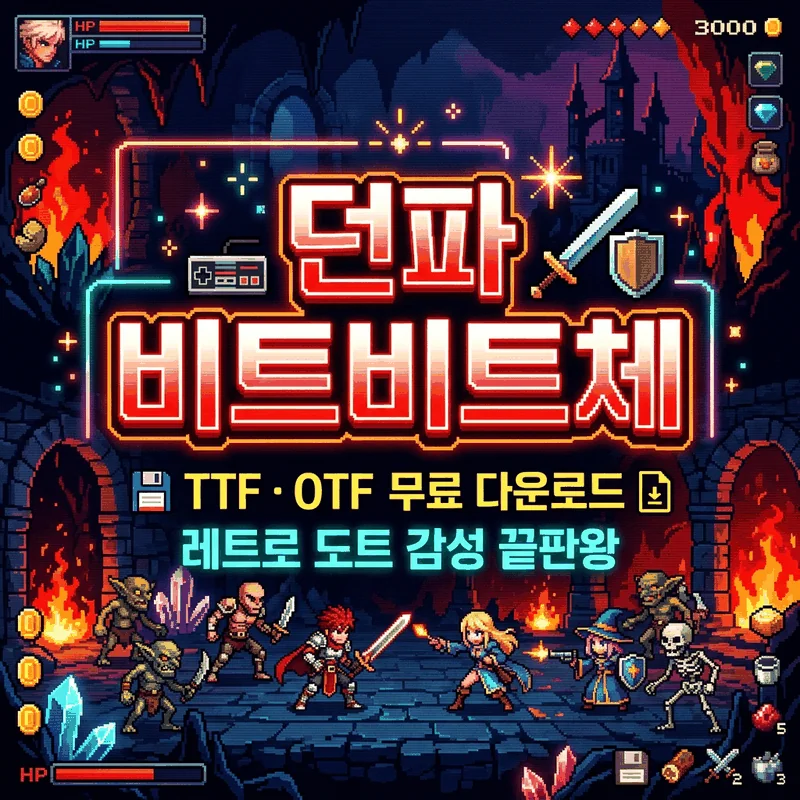
8๋น„ํŠธ ๋ ˆํŠธ๋กœ ๊ฐ์„ฑ์˜ ์ •์  '๋˜ํŒŒ ๋น„ํŠธ๋น„ํŠธ์ฒด v2'์˜ ํŠน์ง•, ๊ณต์‹ ๋‹ค์šด๋กœ๋“œ ๊ฒฝ๋กœ, ์ƒ์—…์  ํ—ˆ์šฉ ๋ฒ”์œ„, ๊ทธ๋ฆฌ๊ณ  ์Šค๋งˆํŠธํฐ ์ ์šฉ๋ฒ•๊นŒ์ง€ ์™„๋ฒฝํ•˜๊ฒŒ ์ •๋ฆฌํ–ˆ์Šต๋‹ˆ๋‹ค.
๋„ํŠธ ๊ฐ์„ฑ, 8๋น„ํŠธ ๊ฐ์„ฑ, ํ”ฝ์…€์•„ํŠธ ์Šคํƒ€์ผ ๋””์ž์ธ์„ ํ•  ๋•Œ ์–ด์šธ๋ฆฌ๋Š” ํ•œ๊ธ€ ํฐํŠธ๋ฅผ ์ฐพ๋‹ค ๋ณด๋ฉด ์„ ํƒ์ง€๊ฐ€ ์ƒ๊ฐ๋ณด๋‹ค ๋งŽ์ง€ ์•Š์Šต๋‹ˆ๋‹ค. ๊ทธ์ค‘์—์„œ๋„ ๋˜ํŒŒ ๋น„ํŠธ๋น„ํŠธ์ฒด๋Š” ์ง„์งœ ๊ฒŒ์ž„ ์ œ์ž‘์‚ฌ์˜ ์›น๋””์ž์ด๋„ˆ๊ฐ€ ์ง์ ‘ ๋งŒ๋“  ์„œ์ฒด๋ผ๋Š” ์ ์—์„œ ๋‹ค๋ฅธ ํ”ฝ์…€ ๊ณ„์—ด ํฐํŠธ์™€ ์ฐจ์›์ด ๋‹ค๋ฆ…๋‹ˆ๋‹ค.
1. ๋˜ํŒŒ ๋น„ํŠธ๋น„ํŠธ์ฒด๋ž€? ํƒ„์ƒ ๋ฐฐ๊ฒฝ ๐Ÿ›๏ธ
๋˜ํŒŒ ๋น„ํŠธ๋น„ํŠธ์ฒด๋Š” (์ฃผ)๋„ค์˜คํ”Œ์ด ์ œ์ž‘ํ•˜๊ณ  ๋„ฅ์Šจ์ฝ”๋ฆฌ์•„๋ฅผ ํ†ตํ•ด ๋ฐฐํฌํ•œ ๋ฌด๋ฃŒ ์„œ์ฒด์ž…๋‹ˆ๋‹ค. ์„œ์ฒด์˜ ํƒ„์ƒ์€ 2020๋…„ 4์›”, ๋˜์ „์•คํŒŒ์ดํ„ฐ ๊ณต์‹ ํ™ˆํŽ˜์ด์ง€์˜ '๋น„ํŠธ๋น„ํŠธ 8๋น„ํŠธ' ๊ฒŒ์ž„ ์†Œ๊ฐœ ํŽ˜์ด์ง€๋ฅผ ๋””์ž์ธํ•˜๋˜ ์›น๋””์ž์ด๋„ˆ์˜ ๊ณ ๋ฏผ์—์„œ ์‹œ์ž‘๋˜์—ˆ์Šต๋‹ˆ๋‹ค.
๋‹น์‹œ 8๋น„ํŠธ ๋ถ„์œ„๊ธฐ๋ฅผ ์™„๋ฒฝํ•˜๊ฒŒ ์ „๋‹ฌํ•  ์ˆ˜ ์žˆ๋Š” ์ ๋‹นํ•œ ํ•œ๊ธ€ ์„œ์ฒด๊ฐ€ ์—†์–ด, ๋””์ž์ด๋„ˆ๊ฐ€ ์ง์ ‘ ๋„ํŠธ ํ˜•ํƒœ๋ฅผ ์‚ด๋ฆฐ ํƒ€์ดํ‹€์„ ์ œ์ž‘ํ•œ ๊ฒƒ์ด ์ง€๊ธˆ์˜ ๋น„ํŠธ๋น„ํŠธ์ฒด๊ฐ€ ๋˜์—ˆ์Šต๋‹ˆ๋‹ค. 2022๋…„ ํ•œ๊ธ€๋‚ ์„ ๊ธฐ๋…ํ•ด ์ผ๋ฐ˜์— ๋ฌด๋ฃŒ ๋ฐฐํฌ๋˜์—ˆ์œผ๋ฉฐ, ํ˜„์žฌ๋Š” ์™„์„ฑ๋„๋ฅผ ๋†’์ธ v2 ๋ฒ„์ „์ด ์ •์‹ ์„œ๋น„์Šค๋˜๊ณ  ์žˆ์Šต๋‹ˆ๋‹ค.
2. ๋น„ํŠธ๋น„ํŠธ์ฒด ํ•ต์‹ฌ ๋””์ž์ธ ํŠน์ง• 4๊ฐ€์ง€ ๐ŸŽฎ
โ‘  ๋„ํŠธ ๊ฐ์„ฑ์˜ ๊ณ„๋‹จ ํ˜•ํƒœ
๋น„ํŠธ๋น„ํŠธ์ฒด์˜ ๊ฐ€์žฅ ํฐ ํŠน์ง•์€ ํš์ด ๊บพ์ด๋Š” ๋ถ€๋ถ„๋งˆ๋‹ค ๋‚˜ํƒ€๋‚˜๋Š” ํ”ฝ์…€ ๊ณ„๋‹จ ๋ชจ์–‘์ž…๋‹ˆ๋‹ค. ๋น„ํŠธ๋งต ํฐํŠธ์ฒ˜๋Ÿผ ๋ณด์ด์ง€๋งŒ ๊ณ ํ•ด์ƒ๋„์—์„œ๋„ ์„ ๋ช…ํ•œ ๋ฒกํ„ฐ ๊ธฐ๋ฐ˜์ด๊ธฐ ๋•Œ๋ฌธ์— ํฐ ์‚ฌ์ด์ฆˆ ๋ฐฐ๋„ˆ์—์„œ๋„ ๋„ํŠธ์˜ ๋ฏธํ•™์„ ๊ทธ๋Œ€๋กœ ์‚ด๋ฆด ์ˆ˜ ์žˆ์Šต๋‹ˆ๋‹ค.
โ‘ก ๋„ค๋ชจ๊ผด์— ๊ฝ‰ ์ฐฌ ๋ณผ๋“œํ•œ ํ˜•ํƒœ
๋„ค๋ชจ๊ผด์— ๊ฝ‰ ์ฐจ๋Š” ๊ตฌ์กฐ๋ฅผ ๊ฐ€์ง„ ๋ณผ๋“œํ•œ ์ œ๋ชฉ์šฉ ์„œ์ฒด์ž…๋‹ˆ๋‹ค. ๊ธ€์ž ํ•˜๋‚˜ํ•˜๋‚˜์˜ ๋ฌด๊ฒŒ๊ฐ์ด ์ข‹์•„ ๊ฐ•์กฐํ•˜๊ณ  ์‹ถ์€ ํƒ€์ดํ‹€์— ์ตœ์ ํ™”๋˜์–ด ์žˆ์Šต๋‹ˆ๋‹ค.
โ‘ข ์„ฌ์„ธํ•œ ์„ค๊ณ„์™€ ๋†’์€ ๊ฐ€๋…์„ฑ
๋‹จ์ˆœํžˆ ๊ณ„๋‹จ ๋ชจ์–‘๋งŒ ๋งŒ๋“  ๊ฒƒ์ด ์•„๋‹ˆ๋ผ, ๊ธ€์ž ๊ตฌ์„ฑ์„ ์‚ด์ง ๊ฒน์น˜๊ฑฐ๋‚˜ ๊ณ„๋‹จ ํฌ๊ธฐ๋ฅผ ๋‹ค๋ฅด๊ฒŒ ์กฐ์ ˆํ•˜์—ฌ ์ „์ฒด์ ์ธ ์ด์งˆ๊ฐ์„ ์ค„์ด๊ณ  ๊ฐ€๋…์„ฑ์„ ๋Œ€ํญ ํ–ฅ์ƒ์‹œ์ผฐ์Šต๋‹ˆ๋‹ค.
โ‘ฃ ๋„‰๋„‰ํ•œ ๊ธ€์ž ์ˆ˜ (3,883์ž ์ด์ƒ)
ํ•œ๊ธ€ ๊ธฐ๋ณธ 2,780์ž์— ์ถ”๊ฐ€์ž 1,103์ž๋ฅผ ์ˆ˜๋กํ•˜์—ฌ ์‹ค๋ฌด ๋””์ž์ธ ์ž‘์—… ์ค‘ ๊ธ€์ž๊ฐ€ ๊นจ์ง€๊ฑฐ๋‚˜ ๋ˆ„๋ฝ๋˜๋Š” ์ผ์„ ๋ฐฉ์ง€ํ–ˆ์Šต๋‹ˆ๋‹ค.
๋น„ํŠธ๋น„ํŠธ์ฒด๋Š” ๊ฒŒ์ž„, ๋ ˆํŠธ๋กœ, ํ…Œํฌ ๊ด€๋ จ ํ…Œ๋งˆ ๋””์ž์ธ์—์„œ ๋…๋ณด์ ์ธ ์กด์žฌ๊ฐ์„ ๋ฐœํœ˜ํ•ฉ๋‹ˆ๋‹ค. ํŠนํžˆ ์œ ํŠœ๋ธŒ ์ธ๋„ค์ผ์—์„œ ๊ฐ•์กฐ ๋ฌธ๊ตฌ๋กœ ์ผ์„ ๋•Œ ์‹œ์ฒญ์ž์˜ ๋ˆˆ๊ธธ์„ ๊ฐ€์žฅ ๋จผ์ € ์‚ฌ๋กœ์žก์Šต๋‹ˆ๋‹ค. ๋‹ค๋งŒ ๋„ํŠธ ํ˜•ํƒœ์˜ ํŠน์„ฑ์ƒ ๊ธด ๋ณธ๋ฌธ๋ณด๋‹ค๋Š” 18px ์ด์ƒ์˜ ํƒ€์ดํ‹€์šฉ์œผ๋กœ ์‚ฌ์šฉํ•˜์‹œ๊ธธ ์ถ”์ฒœํ•ฉ๋‹ˆ๋‹ค.